Khi thiết kế logo, việc Cách kết hợp hai font trong logo miễn phí một cách khéo léo là bí quyết tạo nên sự độc đáo và chuyên nghiệp, ngay cả khi bạn thực hiện miễn phí. Để kết hợp hai font trong logo miễn phí hiệu quả, bạn cần hiểu rõ các nguyên tắc tương phản và hài hòa, đồng thời sử dụng các công cụ thiết kế trực tuyến phổ biến như Canva hay Fotor để thử nghiệm và tìm ra cặp font ưng ý, phù hợp với thông điệp thương hiệu của mình. Bài viết này sẽ cung cấp hướng dẫn chi tiết để bạn tự tin tạo ra một logo ấn tượng với hai font chữ miễn phí.
Tại Sao Việc Kết Hợp Hai Font Trong Logo Lại Quan Trọng?
Việc kết hợp hai font trong logo miễn phí không chỉ là một xu hướng thiết kế mà còn là một chiến lược hiệu quả để truyền tải thông điệp thương hiệu phức tạp hơn. Một logo được thiết kế tốt với sự kết hợp font chữ phù hợp có thể tạo ra tác động mạnh mẽ đến cách khách hàng cảm nhận về doanh nghiệp của bạn.
Vai trò của font chữ trong nhận diện thương hiệu là gì?
Font chữ là một yếu tố then chốt trong bộ nhận diện thương hiệu, giống như màu sắc và hình ảnh. Mỗi kiểu font mang một cá tính riêng, từ cổ điển, sang trọng đến hiện đại, năng động hay thân thiện. Việc lựa chọn font chữ chính xác giúp định hình giọng điệu, tính cách của thương hiệu và tạo dựng sự kết nối cảm xúc với khách hàng. Một font chữ rõ ràng, dễ đọc cũng đảm bảo thông điệp của bạn được truyền tải một cách hiệu quả nhất. Hiểu rõ vai trò này là bước đầu tiên để bạn thực hiện cách kết hợp hai font trong logo miễn phí thành công.
Lợi ích của việc sử dụng hai font trong thiết kế logo là gì?
Sử dụng hai font chữ trong logo mang lại nhiều lợi ích vượt trội:
- Tạo điểm nhấn và phân cấp thông tin: Một font có thể dùng cho tên thương hiệu chính, trong khi font còn lại được dùng cho slogan hoặc mô tả phụ, giúp người xem dễ dàng phân biệt và ghi nhớ thông tin quan trọng.
- Tăng tính độc đáo và cá tính: Sự kết hợp khéo léo giữa hai kiểu font khác nhau giúp logo của bạn nổi bật hơn so với các đối thủ, thể hiện sự sáng tạo và phong cách riêng. Đây là một khía cạnh quan trọng khi bạn tìm cách kết hợp hai font trong logo miễn phí.
- Truyền tải đa chiều thông điệp: Mỗi font có thể đại diện cho một khía cạnh khác nhau của thương hiệu. Ví dụ, một font Serif cổ điển kết hợp với một font Sans-serif hiện đại có thể nói lên sự giao thoa giữa truyền thống và đổi mới.
- Cải thiện tính thẩm mỹ: Khi được kết hợp đúng cách, hai font chữ có thể tạo ra sự cân bằng, hài hòa và thu hút thị giác, làm cho logo trở nên chuyên nghiệp và bắt mắt hơn.
Với những lợi ích này, việc tìm hiểu cách kết hợp hai font trong logo miễn phí trở nên vô cùng giá trị cho bất kỳ ai muốn tạo ra một logo chất lượng mà không tốn chi phí.
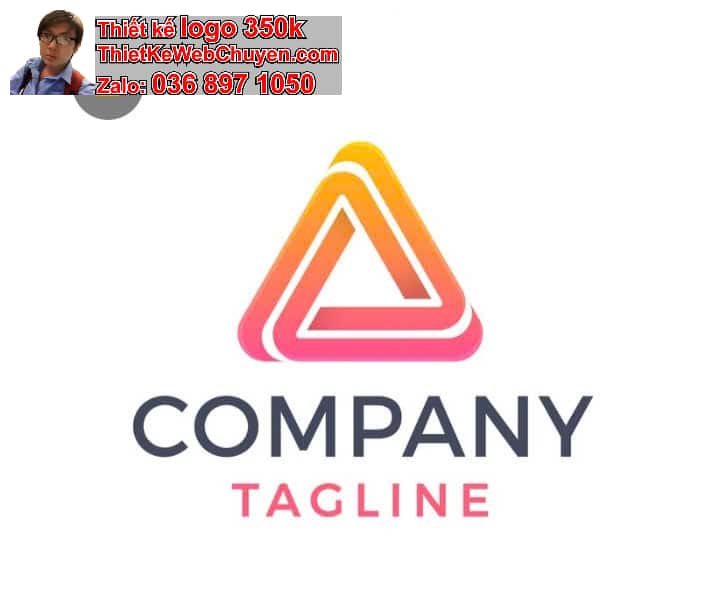
Các Nguyên Tắc Vàng Khi Kết Hợp Hai Font Trong Logo Miễn Phí
Để có được một logo đẹp và hiệu quả với hai font chữ, bạn cần nắm vững những nguyên tắc cơ bản. Đây là nền tảng để bạn áp dụng cách kết hợp hai font trong logo miễn phí một cách chuyên nghiệp.
Làm thế nào để chọn font chính và font phụ phù hợp?
Việc lựa chọn font chính và font phụ là yếu tố quyết định sự thành công của việc kết hợp hai font trong logo miễn phí.
- Tương phản (Contrast): Đây là nguyên tắc quan trọng nhất. Hai font bạn chọn nên có sự khác biệt rõ rệt về một trong các đặc điểm sau:
- Kích thước: Một font lớn, nổi bật và một font nhỏ hơn, bổ trợ.
- Độ đậm nhạt (Weight): Một font đậm (bold) và một font thường (regular) hoặc mỏng (light).
- Kiểu dáng (Style): Kết hợp font Serif (có chân) với Sans-serif (không chân), hoặc Sans-serif với Script (viết tay), hoặc Display (kiểu cách) với Sans-serif. Sự tương phản này giúp mỗi font giữ được cá tính riêng và không bị hòa lẫn vào nhau.
- Mục đích sử dụng: Font chính nên mạnh mẽ, dễ đọc và đại diện cho tên thương hiệu. Font phụ có thể mềm mại hơn, tinh tế hơn, dùng cho slogan hoặc thông tin bổ sung.
- Hài hòa (Harmony): Mặc dù cần tương phản, hai font vẫn phải có một yếu tố nào đó liên kết chúng lại với nhau để tạo ra sự hài hòa tổng thể. Điều này có thể là:
- Tâm trạng/Phong cách: Cả hai font đều mang đến cảm giác hiện đại, cổ điển, vui tươi, hoặc nghiêm túc, ngay cả khi chúng thuộc các kiểu dáng khác nhau.
- Cùng “gia đình” nhưng khác biến thể: Ví dụ, sử dụng một font Sans-serif đậm làm font chính và một biến thể mỏng hơn hoặc nghiêng của cùng họ font đó làm font phụ.
- Mục đích sử dụng và đối tượng mục tiêu: Font chữ phải phản ánh đúng ngành nghề và thông điệp của thương hiệu. Một thương hiệu công nghệ sẽ phù hợp với font hiện đại, sắc nét, trong khi một tiệm bánh thủ công có thể chọn font viết tay hoặc cổ điển. Đây là điều kiện tiên quyết khi bạn thực hiện cách kết hợp hai font trong logo miễn phí.
Những cặp font nào thường được kết hợp hiệu quả?
Dưới đây là một số cặp font kinh điển và hiệu quả mà bạn có thể áp dụng khi tìm cách kết hợp hai font trong logo miễn phí:
- Serif + Sans-serif: Đây là sự kết hợp “kinh điển” và an toàn nhất. Font Serif mang lại cảm giác truyền thống, đáng tin cậy, sang trọng (ví dụ: Georgia, Merriweather, Playfair Display), trong khi Sans-serif tạo sự hiện đại, rõ ràng, dễ đọc (ví dụ: Open Sans, Montserrat, Lato).
- Ví dụ: Tên thương hiệu bằng Playfair Display (Serif), slogan bằng Open Sans (Sans-serif).
- Sans-serif + Script/Handwriting: Sự kết hợp này mang đến vẻ ngoài hiện đại, cá tính và thân thiện. Sans-serif giữ vai trò nền tảng rõ ràng, trong khi font Script thêm vào nét nghệ thuật, sáng tạo, hoặc cảm giác cá nhân (ví dụ: Pacifico, Dancing Script, Great Vibes).
- Ví dụ: Tên thương hiệu bằng Montserrat (Sans-serif), slogan bằng Pacifico (Script).
- Display + Sans-serif: Font Display thường rất nổi bật, độc đáo, và thường được dùng cho tiêu đề lớn. Kết hợp với một Sans-serif đơn giản giúp cân bằng lại sự phức tạp, đảm bảo tính dễ đọc cho các chi tiết nhỏ hơn.
- Ví dụ: Tên thương hiệu bằng Raleway (Display, với những nét đặc trưng), slogan bằng Lato (Sans-serif).
- Font cùng “gia đình” (Superfamily): Một số họ font lớn cung cấp nhiều biến thể (light, regular, bold, italic, condensed) và thậm chí cả phiên bản Serif và Sans-serif. Sử dụng các biến thể từ cùng một họ font đảm bảo sự hài hòa tuyệt đối.
- Ví dụ: Sử dụng Roboto Black (Sans-serif đậm) cho tên thương hiệu và Roboto Light (Sans-serif mỏng) cho slogan, hoặc Roboto Slab (Serif) với Roboto (Sans-serif).
Cần tránh những sai lầm nào khi phối hai font trong logo?
Để đảm bảo thành công trong cách kết hợp hai font trong logo miễn phí, hãy tránh những sai lầm phổ biến sau:
- Sử dụng quá nhiều font: Đây là sai lầm lớn nhất. Chỉ hai font là đủ. Nhiều hơn sẽ khiến logo trở nên lộn xộn, khó đọc và thiếu chuyên nghiệp.
- Chọn hai font quá giống nhau: Nếu hai font không có đủ sự tương phản, chúng sẽ cạnh tranh nhau thay vì bổ trợ, khiến logo trông nhàm chán và không rõ ràng.
- Sử dụng font khó đọc: Mục tiêu hàng đầu của logo là truyền tải thông điệp. Nếu font quá cầu kỳ, quá mỏng, hoặc khoảng cách chữ không hợp lý, logo sẽ mất đi tính hiệu quả.
- Font không phù hợp với ngành nghề/thông điệp: Một font thiếu nghiêm túc cho ngân hàng, hoặc một font quá cứng nhắc cho cửa hàng đồ chơi trẻ em đều là những lựa chọn sai lầm. Font phải phản ánh đúng bản chất của thương hiệu.
- Bỏ qua khoảng cách chữ và dòng: Ngay cả khi bạn đã chọn được cặp font hoàn hảo, việc không điều chỉnh khoảng cách (kerning, tracking, leading) có thể làm hỏng toàn bộ thiết kế. Các công cụ thiết kế logo miễn phí thường có tính năng này.
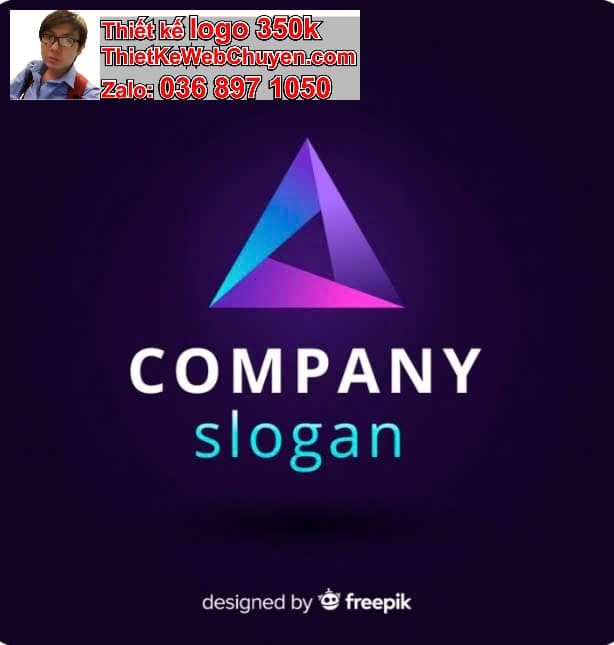
Hướng Dẫn Từng Bước Cách Kết Hợp Hai Font Trong Logo Miễn Phí
Bạn đã nắm vững các nguyên tắc, bây giờ hãy cùng đi vào từng bước cụ thể để thực hiện cách kết hợp hai font trong logo miễn phí một cách hiệu quả.
Bước 1: Xác định thông điệp và đối tượng mục tiêu của logo.
Trước khi bắt đầu tìm kiếm font, hãy dành thời gian để suy nghĩ về bản chất thương hiệu của bạn:
- Thương hiệu của bạn là gì? (Ví dụ: công nghệ, thời trang, ẩm thực, giáo dục, dịch vụ tư vấn.)
- Tính cách thương hiệu là gì? (Ví dụ: hiện đại, truyền thống, sang trọng, thân thiện, vui tươi, chuyên nghiệp, mạnh mẽ.)
- Thông điệp chính bạn muốn truyền tải là gì? (Ví dụ: sự đổi mới, uy tín, sự sáng tạo, sự bền vững.)
- Đối tượng khách hàng mục tiêu của bạn là ai? (Ví dụ: giới trẻ, doanh nhân, gia đình, người lớn tuổi.)
Việc trả lời những câu hỏi này sẽ giúp bạn định hướng phong cách font chữ phù hợp, là bước đệm quan trọng để bạn thực hiện cách kết hợp hai font trong logo miễn phí.
Bước 2: Tìm kiếm và lựa chọn các font miễn phí tiềm năng.
Có rất nhiều nguồn cung cấp font miễn phí chất lượng cao. Khi bạn đã có định hướng phong cách, hãy bắt đầu khám phá:
- Google Fonts: Đây là kho tàng font chữ miễn phí lớn nhất và phổ biến nhất, với giấy phép sử dụng thương mại. Bạn có thể lọc theo kiểu font (Serif, Sans-serif, Display, Handwriting, Monospace) và xem trước cách chúng hiển thị. Google Fonts cũng thường gợi ý các cặp font phù hợp. Đây là một nguồn tài nguyên tuyệt vời cho cách kết hợp hai font trong logo miễn phí.
- DaFont: Cung cấp hàng ngàn font miễn phí, nhưng hãy chú ý kiểm tra giấy phép sử dụng (nhiều font chỉ miễn phí cho mục đích cá nhân).
- Font Squirrel: Một nguồn font miễn phí chất lượng cao được tuyển chọn kỹ lưỡng, tất cả đều có giấy phép sử dụng thương mại.
- Nền tảng thiết kế logo miễn phí: Các công cụ như Canva, Fotor cũng có thư viện font riêng, thường đã được cấp phép sử dụng trong các thiết kế của họ.
Khi tìm kiếm, hãy chọn khoảng 5-7 font tiềm năng cho mỗi vai trò (chính và phụ) dựa trên các nguyên tắc tương phản và hài hòa đã học. Đây là một phần thiết yếu của cách kết hợp hai font trong logo miễn phí.
Bước 3: Thử nghiệm các cặp font và tinh chỉnh.
Đây là giai đoạn bạn biến ý tưởng thành hiện thực. Bạn có thể sử dụng các công cụ thiết kế logo miễn phí trực tuyến để thử nghiệm:
- Canva: Nền tảng này rất dễ sử dụng. Bạn có thể chọn một mẫu logo có sẵn hoặc bắt đầu từ một trang trắng, sau đó thêm văn bản và thay đổi font chữ. Canva cung cấp nhiều lựa chọn font miễn phí và cho phép bạn dễ dàng kết hợp hai font trong logo.
- Fotor: Tương tự Canva, Fotor cũng có trình tạo logo với nhiều tùy chỉnh font.
- LogoMakr: Một công cụ đơn giản cho phép bạn nhanh chóng kéo và thả các yếu tố, bao gồm văn bản với các font khác nhau.
Khi thử nghiệm, hãy chú ý đến:
- Kích thước: Điều chỉnh kích thước của font chính và font phụ để tạo ra sự phân cấp rõ ràng.
- Khoảng cách: Điều chỉnh khoảng cách giữa các chữ cái (kerning) và giữa các dòng (leading) để đảm bảo văn bản dễ đọc và cân đối.
- Màu sắc: Mặc dù bài viết tập trung vào font, màu sắc cũng đóng vai trò quan trọng. Hãy thử các gam màu khác nhau để xem cặp font của bạn hiển thị tốt nhất trong môi trường nào.
- Bối cảnh: Đặt logo của bạn trên các nền khác nhau (trắng, đen, màu) để kiểm tra khả năng hiển thị.
Hãy kiên nhẫn thử nghiệm nhiều cặp và biến thể khác nhau. Mục tiêu là tìm ra sự kết hợp không chỉ đẹp mắt mà còn hiệu quả trong việc truyền tải thông điệp. Đây là bước then chốt trong cách kết hợp hai font trong logo miễn phí.
Bước 4: Đánh giá và nhận phản hồi.
Khi bạn đã có một vài lựa chọn ưng ý về cách kết hợp hai font trong logo miễn phí, đừng ngần ngại chia sẻ chúng với bạn bè, đồng nghiệp hoặc đối tượng khách hàng tiềm năng.
- Thu thập ý kiến: Hỏi họ cảm nhận gì về logo, thông điệp mà nó truyền tải, và liệu có dễ đọc hay không.
- Tự đánh giá: Đứng lùi lại và nhìn logo với con mắt khách quan. Nó có chuyên nghiệp không? Có dễ nhớ không? Có độc đáo không?
- Kiểm tra trên các ứng dụng thực tế: Thử đặt logo lên mockups (tạm thời) của các vật phẩm thực tế như danh thiếp, website, áo phông để xem nó trông như thế nào.
Phản hồi là vô giá để bạn tinh chỉnh cuối cùng và đảm bảo rằng logo của bạn không chỉ đẹp mà còn hiệu quả trong thực tế.
Các Công Cụ Giúp Bạn Kết Hợp Hai Font Trong Logo Miễn Phí Hiệu Quả Nhất
Để việc kết hợp hai font trong logo miễn phí trở nên dễ dàng và chuyên nghiệp, bạn không thể bỏ qua các công cụ thiết kế trực tuyến mạnh mẽ này.
Canva: Nền tảng thiết kế logo miễn phí đa năng.
Canva là một trong những công cụ phổ biến nhất cho người không chuyên. Với thư viện mẫu logo phong phú và hàng ngàn font chữ miễn phí, bạn có thể dễ dàng:
- Chọn mẫu hoặc bắt đầu từ đầu: Canva cung cấp vô số mẫu logo được thiết kế sẵn. Bạn chỉ cần chọn một mẫu ưng ý và thay đổi văn bản, font chữ, màu sắc.
- Dễ dàng thay đổi font: Giao diện kéo thả trực quan cho phép bạn nhanh chóng chọn và thay đổi font cho từng phần văn bản.
- Khám phá cặp font: Mặc dù không có tính năng gợi ý cặp font chuyên biệt, bạn có thể thử nghiệm các font phổ biến đã được sử dụng trong các mẫu của Canva để tìm cảm hứng.
- Lưu và tải xuống: Bạn có thể tải xuống logo ở các định dạng phổ biến như PNG, JPG, PDF.
Canva là lựa chọn tuyệt vời để bạn thực hành cách kết hợp hai font trong logo miễn phí một cách nhanh chóng và hiệu quả.
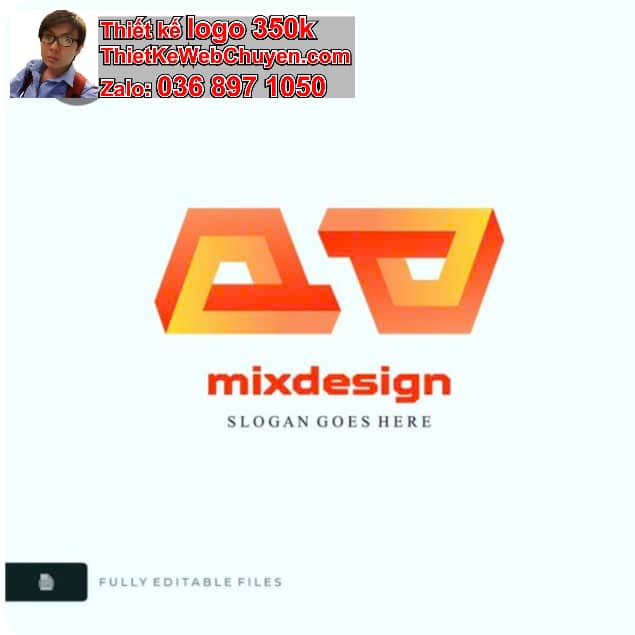
Fotor: Công cụ tạo logo với nhiều tùy chỉnh font.
Fotor cũng là một trình tạo logo trực tuyến mạnh mẽ, cung cấp nhiều tính năng tương tự Canva nhưng có thể có giao diện hoặc thư viện font khác biệt một chút.
- Thư viện font đa dạng: Fotor có bộ sưu tập font chữ riêng, bao gồm nhiều lựa chọn miễn phí phù hợp cho việc kết hợp hai font trong logo miễn phí.
- Tùy chỉnh linh hoạt: Bạn có thể điều chỉnh kích thước, màu sắc, độ trong suốt, khoảng cách chữ, và nhiều yếu tố khác của văn bản để tạo ra sự kết hợp font hoàn hảo.
- Giao diện thân thiện: Tương tự Canva, Fotor được thiết kế để dễ sử dụng cho mọi đối tượng người dùng.
LogoMakr: Đơn giản, trực quan để kết hợp font.
LogoMakr là một công cụ đơn giản hơn, tập trung vào việc tạo logo nhanh chóng. Nó ít phức tạp hơn Canva hay Fotor, nhưng vẫn đủ mạnh để bạn thử nghiệm cách kết hợp hai font trong logo miễn phí.
- Đơn giản hóa quy trình: Bạn có thể tìm kiếm biểu tượng, thêm văn bản và chọn font một cách nhanh chóng.
- Tải xuống miễn phí (chất lượng thấp): LogoMakr cho phép bạn tải xuống phiên bản chất lượng thấp miễn phí, đủ để xem trước hoặc sử dụng cho mục đích phi thương mại. Phiên bản chất lượng cao hơn thường yêu cầu trả phí.
Font Combinator / Fontjoy (online tools to suggest pairs).
Mặc dù không phải là trình tạo logo đầy đủ, các công cụ này rất hữu ích cho bước tìm kiếm và lựa chọn cặp font tiềm năng.
- Font Combinator: Cho phép bạn chọn hai font và xem chúng hiển thị cùng nhau như thế nào, với các tùy chỉnh về kích thước và văn bản. Rất hữu ích để hình dung cách kết hợp hai font trong logo miễn phí.
- Fontjoy: Đây là một công cụ dựa trên AI, tự động đề xuất các cặp font hài hòa hoặc tương phản, giúp bạn khám phá những sự kết hợp mà bạn có thể chưa nghĩ đến. Bạn có thể “khóa” một font mình thích và để AI gợi ý font còn lại.
Sử dụng kết hợp các công cụ này sẽ giúp bạn tối ưu hóa quá trình thiết kế và tìm ra cách kết hợp hai font trong logo miễn phí tốt nhất.
Bí Quyết Nâng Cao Kỹ Năng Kết Hợp Hai Font Trong Logo Của Bạn
Để không ngừng cải thiện khả năng kết hợp hai font trong logo miễn phí và tạo ra những thiết kế thực sự ấn tượng, hãy ghi nhớ những bí quyết sau:
Nghiên cứu các logo thành công.
Hãy dành thời gian quan sát và phân tích các logo của những thương hiệu lớn, nổi tiếng.
- Học hỏi từ chuyên gia: Xem cách họ sử dụng font chữ, cách họ kết hợp hai font (hoặc nhiều hơn nếu có) để truyền tải thông điệp.
- Phân tích nguyên tắc: Cố gắng tìm hiểu tại sao một cặp font lại hoạt động hiệu quả trong một logo cụ thể – có phải vì sự tương phản, hài hòa, hay phù hợp với ngành nghề?
- Tìm cảm hứng: Mục đích không phải là sao chép mà là tìm kiếm nguồn cảm hứng, học hỏi các kỹ thuật và áp dụng chúng vào việc kết hợp hai font trong logo miễn phí của riêng bạn.
Luôn ưu tiên tính dễ đọc.
Dù bạn muốn tạo ra một logo sáng tạo đến đâu, tính dễ đọc luôn phải là ưu tiên hàng đầu.
- Đảm bảo rõ ràng: Một logo chỉ hiệu quả khi thông điệp của nó được truyền tải rõ ràng và dễ hiểu.
- Kiểm tra trên các kích thước khác nhau: Logo của bạn có dễ đọc khi nó rất nhỏ trên danh thiếp hoặc rất lớn trên biển quảng cáo không? Đây là một thử thách quan trọng khi bạn tìm cách kết hợp hai font trong logo miễn phí.
- Tránh font quá cầu kỳ: Đặc biệt là cho font chính hoặc slogan. Font Script đẹp mắt có thể khó đọc khi kích thước nhỏ.
Đừng ngại thử nghiệm.
Thiết kế là một quá trình sáng tạo và khám phá. Đừng ngần ngại thử nghiệm nhiều sự kết hợp khác nhau, ngay cả những cặp có vẻ “kỳ lạ”.
- Khám phá những điều mới: Đôi khi, những sự kết hợp bất ngờ lại tạo ra hiệu quả thị giác độc đáo.
- Lưu lại các phiên bản: Khi thực hiện cách kết hợp hai font trong logo miễn phí, hãy lưu lại các phiên bản khác nhau của logo để bạn có thể so sánh và quay lại nếu cần.
- Học từ sai lầm: Không phải mọi thử nghiệm đều thành công, nhưng mỗi lần thử là một cơ hội để học hỏi và cải thiện.
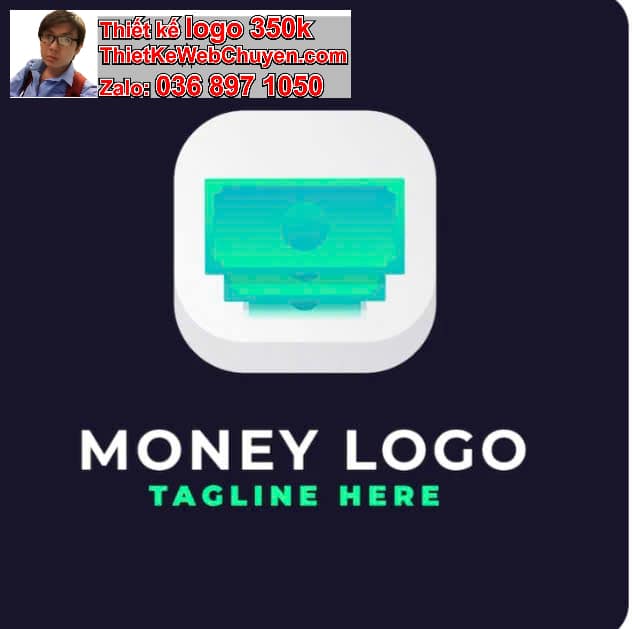
Giới hạn màu sắc.
Mặc dù trọng tâm là font chữ, nhưng màu sắc cũng ảnh hưởng lớn đến tổng thể logo.
- Giữ màu sắc đơn giản: Khi bạn đang tập trung vào việc kết hợp hai font trong logo miễn phí, hãy giữ bảng màu đơn giản (thường là 1-3 màu) để không làm phân tán sự chú ý khỏi font chữ.
- Đảm bảo độ tương phản màu sắc: Font chữ phải nổi bật trên nền, bất kể màu sắc bạn chọn.
FAQ: Các Câu Hỏi Thường Gặp Về Cách Kết Hợp Hai Font Trong Logo Miễn Phí
Để giúp bạn giải đáp những thắc mắc thường gặp nhất khi thực hiện cách kết hợp hai font trong logo miễn phí, chúng tôi đã tổng hợp các câu hỏi và câu trả lời dưới đây.
Có nên sử dụng nhiều hơn hai font trong logo không?
Không nên. Nguyên tắc chung trong thiết kế logo là giới hạn số lượng font chữ. Sử dụng quá nhiều font (thường là hơn hai) sẽ làm cho logo trở nên lộn xộn, khó đọc và thiếu chuyên nghiệp. Hai font là con số lý tưởng để tạo sự tương phản và phân cấp thông tin mà vẫn giữ được sự tinh tế và dễ hiểu. Một font chính cho tên thương hiệu và một font phụ cho slogan hoặc thông tin bổ sung là đủ để tạo điểm nhấn hiệu quả cho logo của bạn khi bạn tìm cách kết hợp hai font trong logo miễn phí.
Làm thế nào để tìm được font miễn phí có giấy phép sử dụng thương mại?
Để đảm bảo bạn có thể sử dụng logo của mình cho mục đích kinh doanh mà không vi phạm bản quyền, hãy tìm font có giấy phép sử dụng thương mại (commercial license). Các nguồn tốt nhất bao gồm:
- Google Fonts: Tất cả các font trên Google Fonts đều miễn phí và có giấy phép sử dụng thương mại. Đây là lựa chọn hàng đầu cho cách kết hợp hai font trong logo miễn phí.
- Font Squirrel: Trang web này chỉ tuyển chọn các font miễn phí 100% cho mục đích thương mại.
- Adobe Fonts: Nếu bạn có gói Adobe Creative Cloud, bạn có quyền truy cập vào thư viện Adobe Fonts khổng lồ, tất cả đều có giấy phép thương mại.
- Kiểm tra giấy phép: Khi tải font từ các nguồn khác như DaFont, hãy luôn kiểm tra file giấy phép đi kèm (thường là file .txt) hoặc mô tả trên trang web để xác nhận quyền sử dụng.
Kết hợp font serif và sans-serif có phải là lựa chọn an toàn không?
Hoàn toàn là một lựa chọn an toàn và rất được khuyến khích. Sự kết hợp giữa font Serif (có chân) và Sans-serif (không chân) là một trong những kỹ thuật phối font kinh điển và hiệu quả nhất trong thiết kế. Font Serif thường mang lại cảm giác truyền thống, uy tín, và sang trọng, trong khi font Sans-serif thể hiện sự hiện đại, rõ ràng và dễ đọc. Sự tương phản này tạo ra sự cân bằng hoàn hảo, giúp mỗi font nổi bật và bổ trợ cho nhau, làm cho việc kết hợp hai font trong logo miễn phí của bạn trở nên chuyên nghiệp và dễ hiểu.
Có công cụ nào tự động kết hợp font cho logo không?
Có, một số công cụ có thể gợi ý hoặc hỗ trợ bạn trong việc kết hợp font, dù không hoàn toàn tự động tạo ra một logo hoàn chỉnh.
- Fontjoy: Đây là một công cụ online sử dụng thuật toán để gợi ý các cặp font hài hòa hoặc tương phản. Bạn có thể “khóa” một font bạn thích và nó sẽ đề xuất các font khác phù hợp.
- Canva và Fotor: Mặc dù không tự động tạo cặp font, các nền tảng này có sẵn nhiều mẫu logo đã được thiết kế sẵn với các cặp font được phối hợp chuyên nghiệp, bạn có thể tham khảo và học hỏi.
- Các trình tạo logo AI (trả phí): Một số trình tạo logo dựa trên AI (thường là trả phí) có thể tự động đề xuất cặp font dựa trên thông tin bạn cung cấp về thương hiệu. Tuy nhiên, để kết hợp hai font trong logo miễn phí, bạn sẽ cần tự mình thử nghiệm nhiều hơn với các công cụ kể trên.
Kết hợp hai font trong logo không còn là một nhiệm vụ khó khăn khi bạn nắm vững các nguyên tắc và biết cách sử dụng các công cụ miễn phí. Bằng cách áp dụng cách kết hợp hai font trong logo miễn phí mà chúng tôi đã hướng dẫn, bạn sẽ có thể tạo ra một logo không chỉ đẹp mắt mà còn hiệu quả trong việc truyền tải thông điệp thương hiệu.